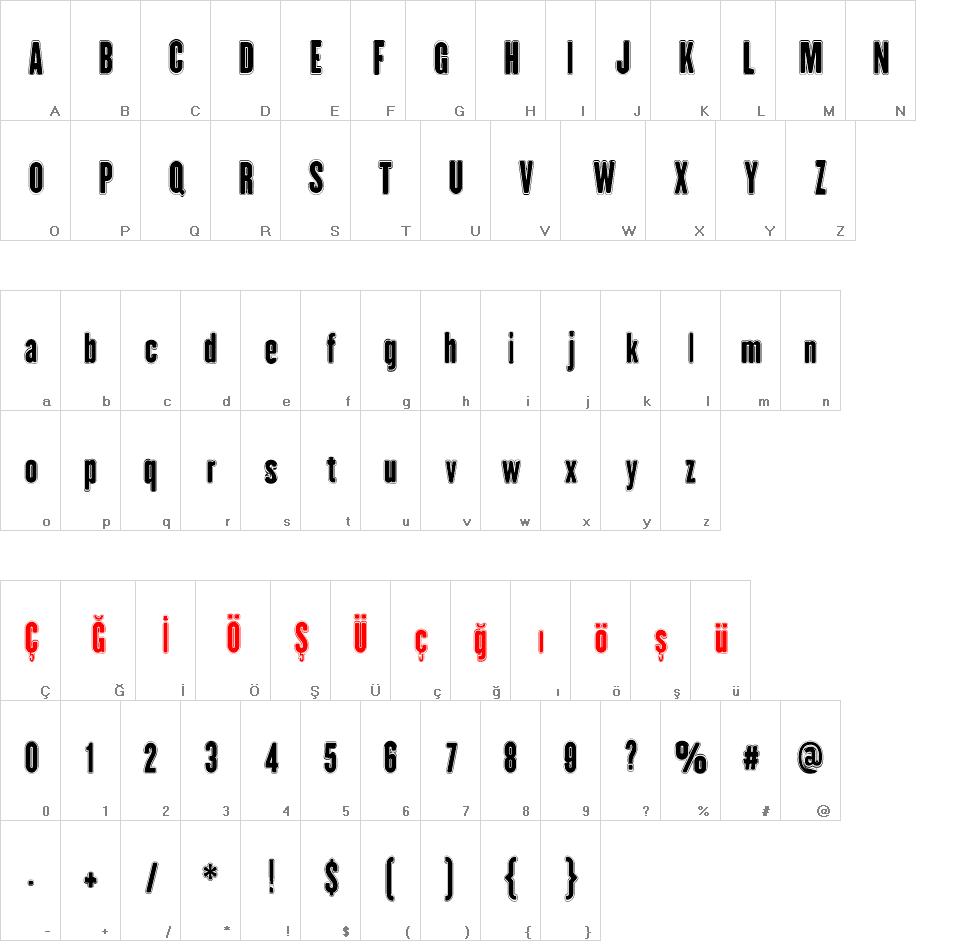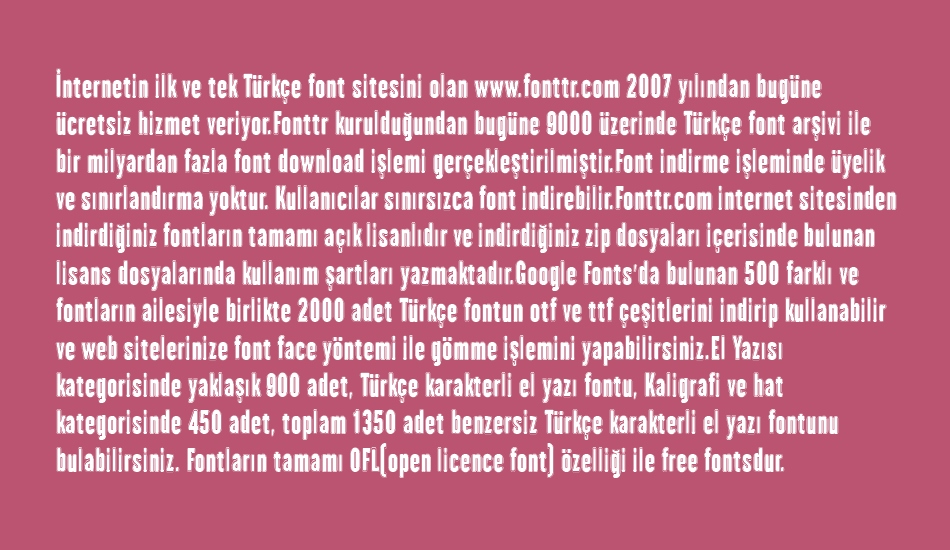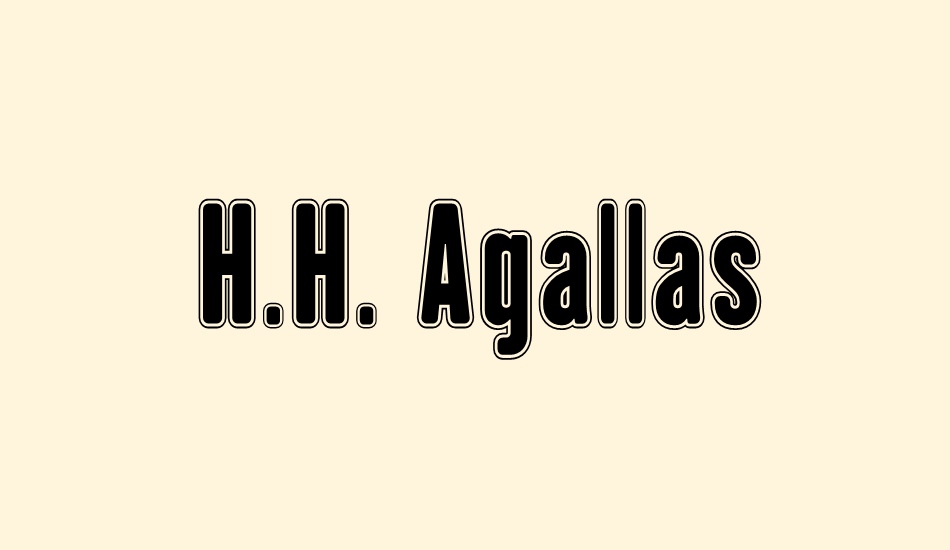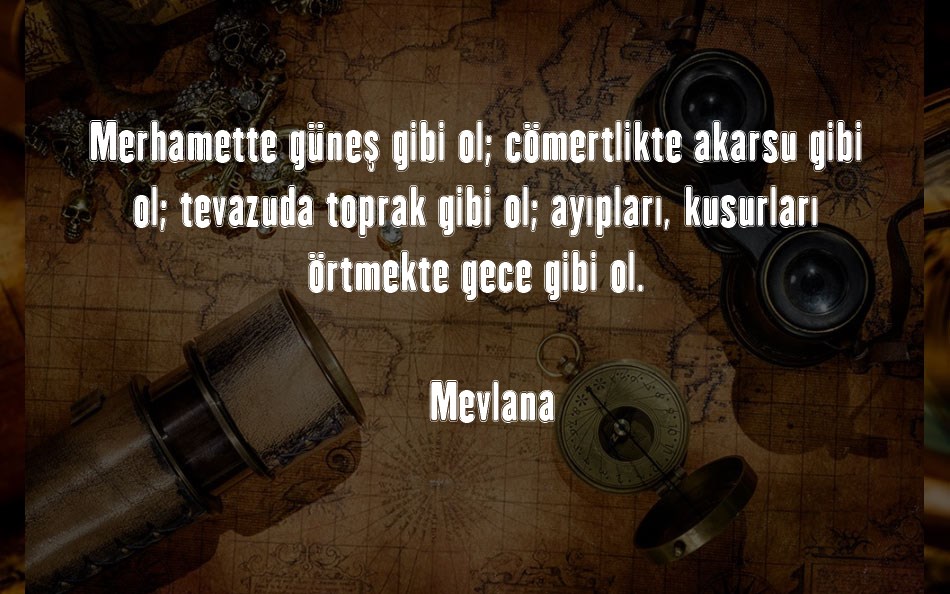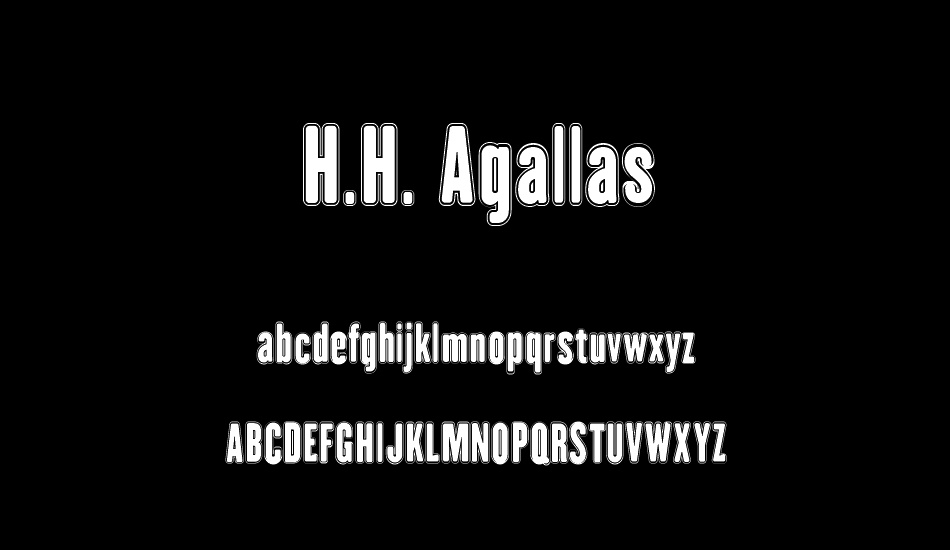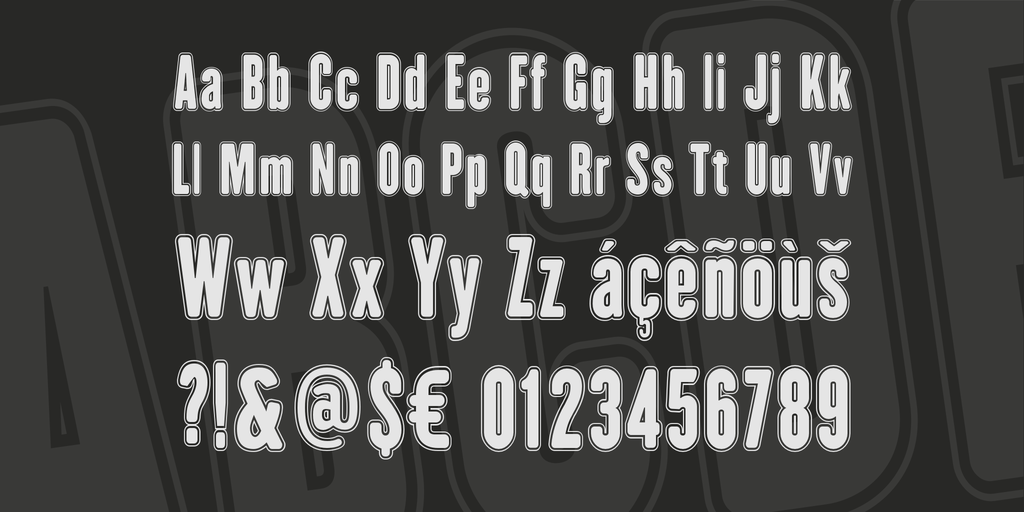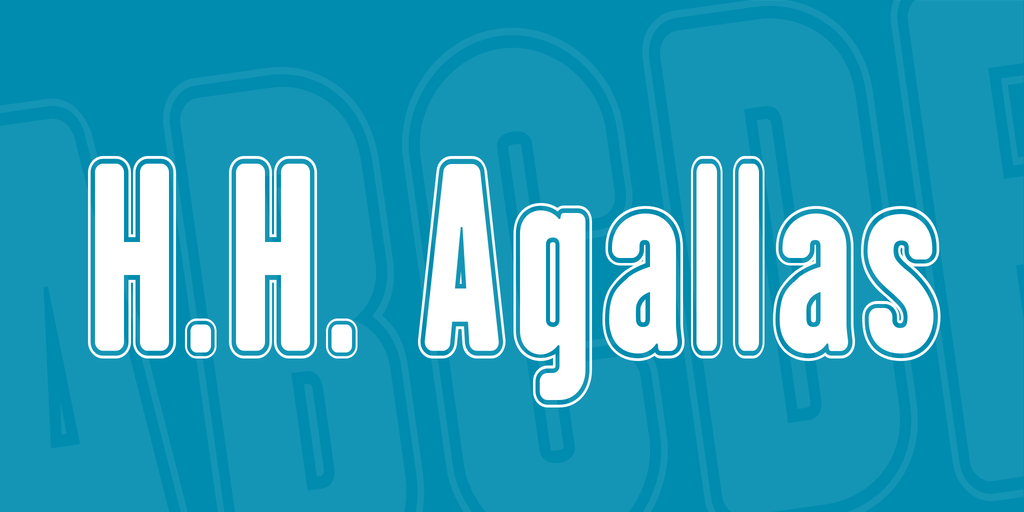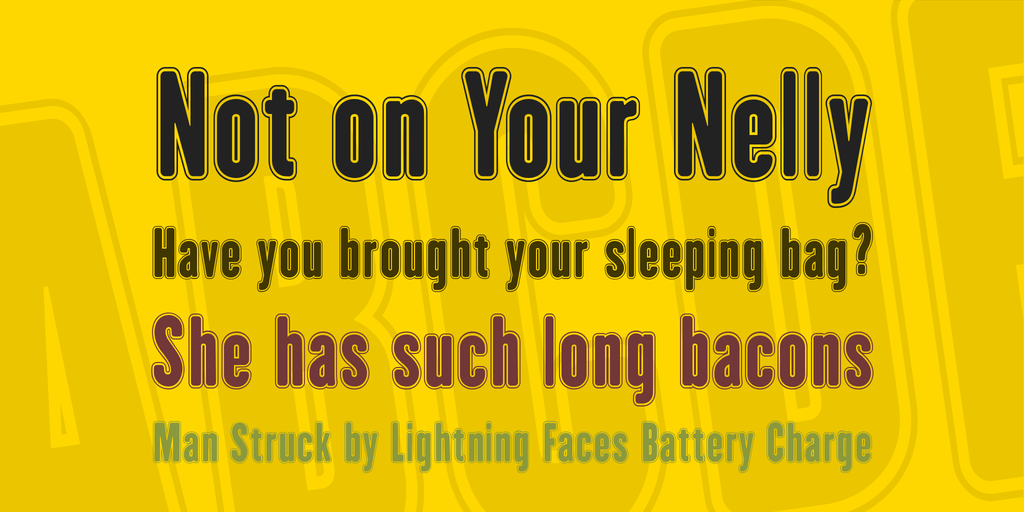
H.H. Agallas font
Esta tipografía es una versión universitaria de mi anterior H.H. Samuel, como mi sobrino comienza la universidad este año le he construido esta fuente de estilo college a la que he puesto el nombre de su Epagneul Breton, fiel amigo y compañero: Agallas.